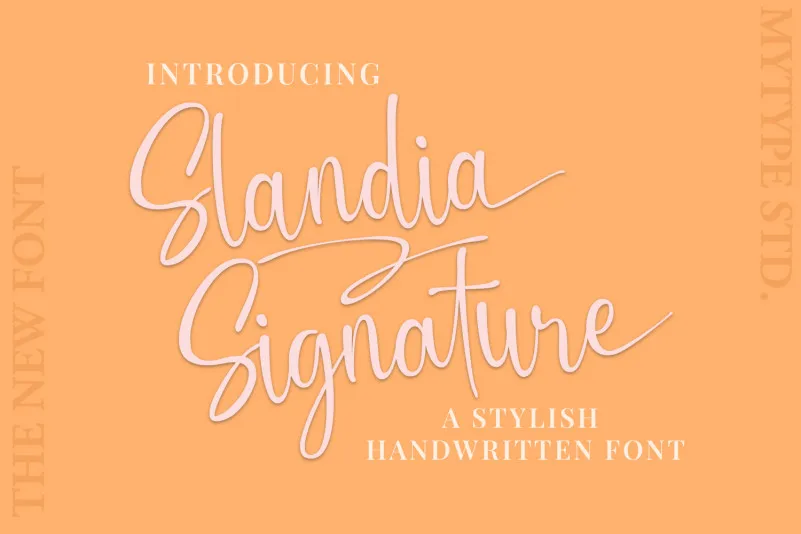
Esta é uma fonte escrita à mão que transmite um toque delicado e eterno. É a escolha perfeita para criar logomarcas memoráveis, identidades visuais inovadoras e frases inspiradoras. Cada letra tem uma única e linda personalidade, fazendo com que seu design ganhe vida! Esta fonte é PUA encoded, o que significa que você pode acessar todos os gráficos e tirones sem esforço. É perfeito para projetos que valorizam a autenticidade e a arte manual. Slandia Signature Font oferece um toque de sofisticação que não deixará ninguém indiferente.